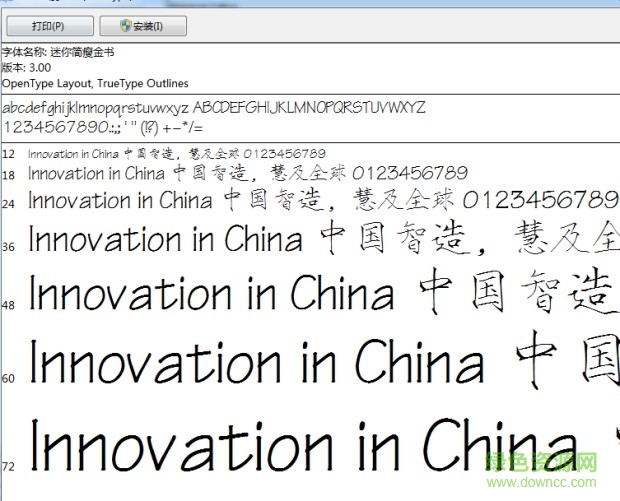
jsoujingsu字體又叫迷你簡瘦金書字體,該字體同時支持mac系統(tǒng)和Windows系統(tǒng),行筆細(xì)勁,筆畫鋒利,勁挺美觀,功力深厚,具有古籍行書的風(fēng)貌,需要的朋友快來綠色資源網(wǎng)下載吧!
特點(diǎn)是運(yùn)筆直如矢,勁如鐵,橫劃收筆帶鉤,豎劃收筆帶點(diǎn),結(jié)體縱伸橫逸,狹瘦勁挺,排印小字時和現(xiàn)代硬筆書法字體有異曲同工之妙。
比較有名的有《怪石詩貼》《牡丹》《風(fēng)霜》《大觀圣作碑》《楷書千字文》《秾芳詩》《夏日詩貼》《神霄玉清萬壽宮詔》《瘦金體草書千字文》等